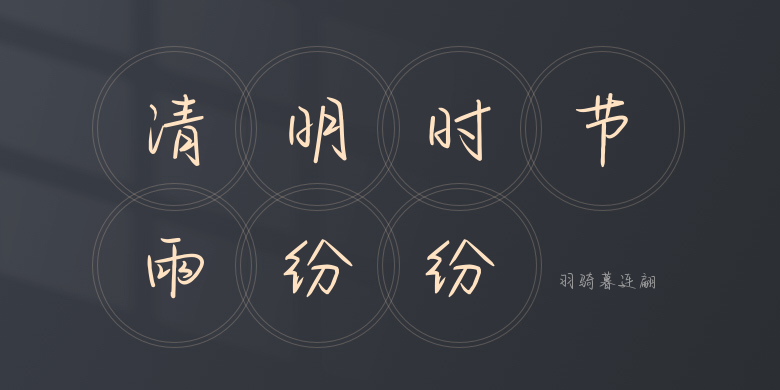
羽骑暮连翩
羽骑暮连翩,这款字体结构工整、笔画清晰,兼顾美观与易读性,适用于标题、正文、海报、包装、LOGO 等多种场景。字形优雅稳定,风格百搭耐看,适配日常排版与创意设计,让文字呈现更舒适、更具质感。羽骑暮连翩一笔一画,皆是细节,以均衡的比例、流畅的线条打造舒适视觉体验,字形端正大气,风格简约现代。无论是商业设计、品牌宣传还是日常排版,都能轻松驾驭,让文字更有格调与力量。羽骑暮连翩字体下载。